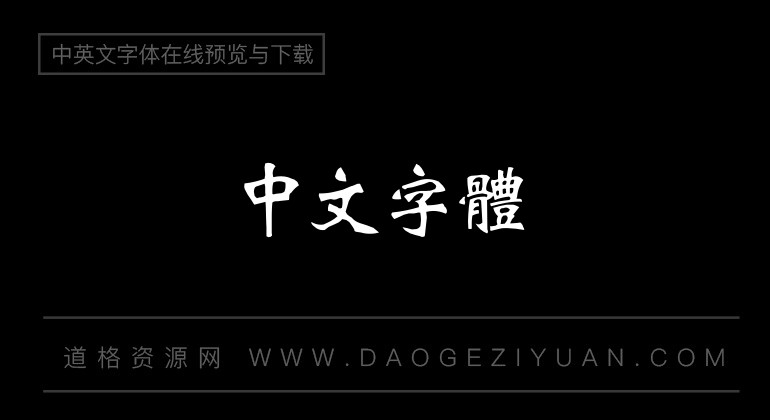
四通利方魏碑体繁
四通利方魏碑体繁是一款由中国著名字体设计师魏碑先生设计的行书字体,它采用了中国传统的四通利方魏碑的书法结构,结合现代技术的精细化设计,把标准的汉字书写工艺与传统书法的美感结合在一起,使字体更加精美,更加优雅,更具有传统书法的美感。
四通利方魏碑体繁是一款非常不错的手写艺术字体,具有很好的视觉感,适合于文化类的宣传设计、商业类品牌的广告和产品包装设计以及个性化文字排版等较多场景。